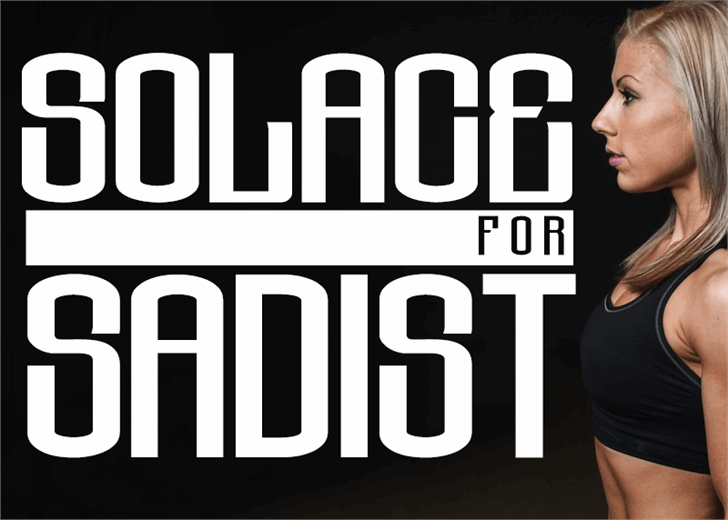
A fonte Solace For Sadist é uma escolha perfeita para aqueles que buscam algo leve e versátil na mistura de linhas e espaçamentos da sans-serif. Este design, criado pelo talentoso Hamilton, oferece um toque moderno e minimalista em qualquer projeto gráfico onde você precise de uma fonte clara e fácil de ler. Suas linhas finas e bem balanceadas permitem que o texto seja visualmente atraente sem perder sua legibilidade, tornando-a perfeita para textos de intruções ou apresentações corporativas. Com seu design suave e despojado, Solace For Sadist não apenas reforça seu valor como fonte, mas também complementa sua personalidade no ambiente onde ela é usada. Este é um verdadeiro tesouro do mundo dos recursos gráficos, uma escolha de fonte que merece ser explorada em seus trabalhos futuros.